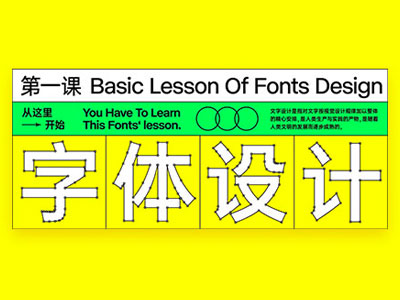
学习字体设计前,先补上这份超全面的字体基础知识
Hello,大家好,我们在做设计的时候总离不开字体,可是多如牛毛的字库字体里,免费的只有那么几个,难以满足我们的工作需求。铤而走险的话又会容易招到律师函警告,那么怎么办呢?最直接粗暴的方式就是学会字体设计,需要用什么字体就做什么字体,自己动手,丰衣足食。那么学习字体设计应该从哪里开始学呢?今天的这节课,我们就为你开启字体设计的新大门,给你们介绍一些最基础最基础的字体设计知识。
首先,我们来了解一下字体设计的三个原则,第一个是易辨性,易辨性指的是我们设计的文字要易于识别。
可读性是指当我们设计了一套的字体,我们将他们放在一起之后,是否能够让人流畅、舒适的阅读。
艺术性是指字体的表现力与美观程度,作为字体设计师,好看的字体肯定是我们所追求的。
当然,不同情境下的字体对这三个原则的要求都是不同的。例如高速公路上的指示路牌,需要将易辨性做到极致。
日本就为了高速路的路牌专门设计了一款字体。
我们来看看这一套字体,他的中宫非常的大,并且省略掉了非常多不影响识别度的细节。为的就是让这款字体在极短的时间内就可以被识别。
而对于书籍里的大段文字,最主要追求的则是可读性,降低人在大量阅读时产生的疲惫感。
对于海报上的标题字来说,艺术性则是相对最重要的,因为海报标题需要足够的有张力和美观才能够吸引受众的注意。但是海报也得保证一定的易辨性,完全丢失易辨性的海报就失去了他原本传达的作用。
不过对于一些玄之又玄的艺术作品来说,易辨性和可读性就不是那么重要了。但是设计师毕竟不是纯粹的艺术家,我们面对的受众是普罗大众,我们做字体设计的时候还是需要尽可能的保证易辨性和可读性。
对于字体设计来说,易辨性、可读性和艺术性这三个原则是非常重要的,有许多初学字体设计的设计师总会忽略掉这三个原则,为了追求视觉上的效果,对文字的结构、笔画进行大幅度的变动,导致文字的识别性大大降低,而且最后做出来的效果也并不美观。那么初学字体设计的我们应该怎么避免这种情况呢?很简单,我们要先把字体的基础打扎实,先不要追求变化。接下来我们就给大家讲解一些汉字的笔画结构以及其他基础知识。
大家还记得我们小学第一节语文课学的是什么吗?没错,学的就是笔画和字体结构。接下来我就带着大家一起来回顾一下这些已经被我们遗忘了的小学知识。
讲汉字笔画的话我们不得不提到相传王羲之所创造的永字八法。
永字八法将永字拆分为了八个笔画,分别为,侧、勒、弩、趯、策、掠、啄、磔。
他们分别对应点、横、竖、钩、提、撇、短撇和捺。
到了现代,永字八法演变成了现代的八个基本笔画(点、横、竖、撇、捺、提、折、钩),原来的短撇被折所取代了。
通过这八个基本的笔画,我们可以组合出更多复杂的笔画。
接着我们来回顾一下字体的结构,我们可以将字体按照结构分为单体字、上下结构、上中下结构、左右结构、左中右结构、半包围结构、全包围结构和镶嵌结构。
上面我们讲的都是小学课本里学过的字体知识,接下来我们就给大家传授一些新的知识。字身框是字体外侧的一个假想框,他代表了我们在电脑里打出一个文字所占的大小。
他的概念来源于铅字印刷,指的是刻着文字的模型的外轮廓。
在字身框的内部还会有一个字面框,字面框才是代表文字字形的实际大小,我们一般在做字之前都会先设定一个字面框作为设计的参考。
如果我们将两个字的字身框紧贴在一起,这两个字的字面框之间的距离就是字间距。
接着我们来讲解重心,重心指的是字的视觉平衡点,在字体设计中,重心是非常重要的一个概念。那么我们应该怎么判断一个字的重心在哪里呢?
按照物理学里的方法,我们将字找两个不同的点悬挂起来,沿着悬挂的绳子画直线。那么这两条直线的交叉点就是这个字的重心。但是我们做字体设计的时候不可能按照这样的方式去测量字体的重心,我们只要大致的目测一下,重心的位置是靠上还是靠下就可以了。
中宫是字体设计中另外一个很重要的概念。它来源于书法中的九宫格,是九宫格最中间的一格。
后来演变成了字体重心周围的一片区域,我们通常用中宫的大小来衡量汉字笔画的疏密程度。
对于像繁体「東」字这样中间有一个封闭空间的汉字,我们就可以通过这个空间的大小来判断汉字的中宫大小。
那么如果是像「南」字这种没有封闭空间的字体来说,我们应该怎么样判断中宫的大小呢?这里我们介绍一个新的概念,叫做字白。字白指的是笔画之间和外围的白空间,也就是字身框内除去文字的部分。
字白中,笔画之间形成的包围或者半包围的白空间,我们称之为字腔。
而笔画之间其他的未封闭的空间就叫做字谷,通过字腔和字谷的大小,就可以判断出中宫的大小了。
中心线相信很好理解了,就是字面框垂直和水平方向上,中间的两条线。
对于左右结构和上下结构来说,我们还可以画出第二中心线来确定偏旁部首的位置。
文字的骨骼指的是字体笔画的中心线,他和人的骨骼类似,人的骨骼决定了人的高矮,而文字的骨骼则决定了文字的重心、中宫和高矮胖瘦等。
那么有骨骼肯定就得有皮肉,文字中的皮肉叫做体饰,指的是笔画中的装饰部分,决定了字体的外观。
在字体设计中有一句行话,叫做骨骼大于体饰,什么意思呢?就是一个字的骨骼搭得好,那么他体饰即使没那么好看,这个字看上去也像那么回事。可是如果这个字的骨骼本身就很难看,不稳,那么体饰无论再怎么变,这个字也很难变得好看。前面说到骨骼与文字的字面、中宫和重心有紧密的联系,下面我们就给大家介绍一下,骨骼是怎么样影响文字的气质的。
那我们先来看看字面,我们还是用这个東字来做示范。字面可以分为窄体、宽体和正常体。
不知道大家有没有看过指环王,字面宽的字体就像是电影里虽然很矮但是非常强壮的矮人战士,他给人力量感和稳重的印象。
而字面窄的字体就像是高挑纤瘦的精灵王子,灵动、优雅是他的特征。
接着我们来分析一下重心。这三个東字分别重心偏下,重心在中间和重心偏上。重心的高低可以类比人的腿长,重心越高,腿越长。
所以重心偏高的字体就像是腿超长的超模,给人一种秀丽的印象。